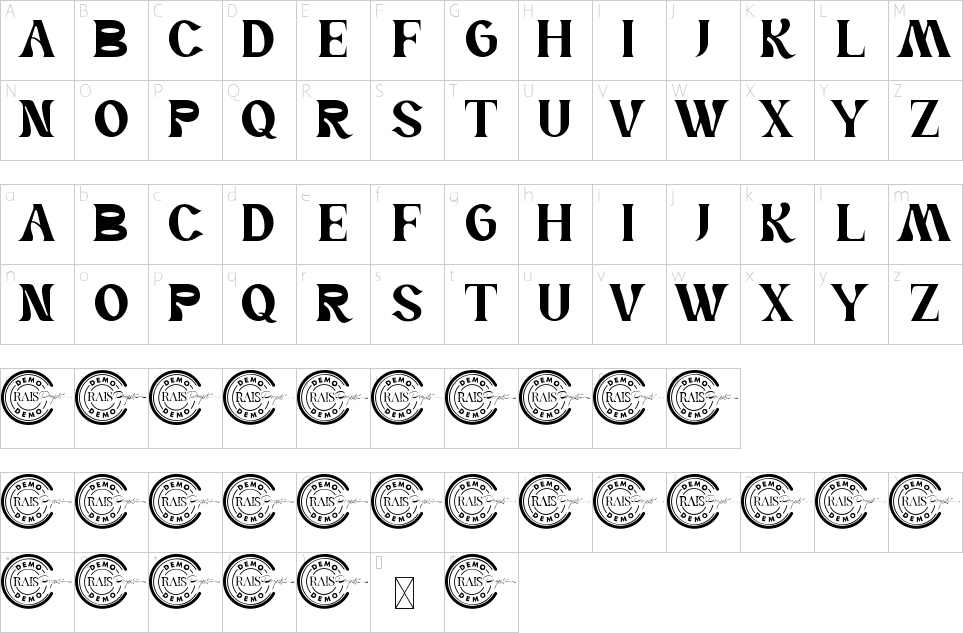
A Power Passion é uma fonte elegante e vibrante, projetada por RaisProject, disponível gratuitamente tanto para Windows quanto para Mac. Suas linhas suaves e seus tons vibrantes a tornam um complemento perfeito para qualquer layout de design gráfico. Através de sua capacidade de expressar emoções fortes e poderosas de uma maneira sofisticada, a Power Passion se destaca como uma opção interessante para qualquer projeto que exija uma fonte poderosa e vibrante. Esta fonte foi baixada mais de 2,207 vezes, demonstrando sua popularidade e eficácia. A Power Passion é um elemento adicional de estilo que certamente enriquecerá qualquer projeto de design.